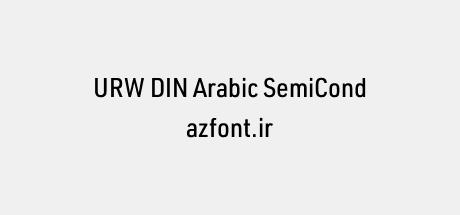
URW DIN Arabic SemiCond
فونت زیبای رایگان URW DIN Arabic SemiCond
قلم زیبای URW DIN Arabic SemiCond Medium از سری قلم های بسیار زیبا برای تایپوگرافی و لوگو تایپ می باشد.این قلم در وزن Medium و توسط Volker Schnebel / Arlette Boutros طراحی و منتشر شده است.